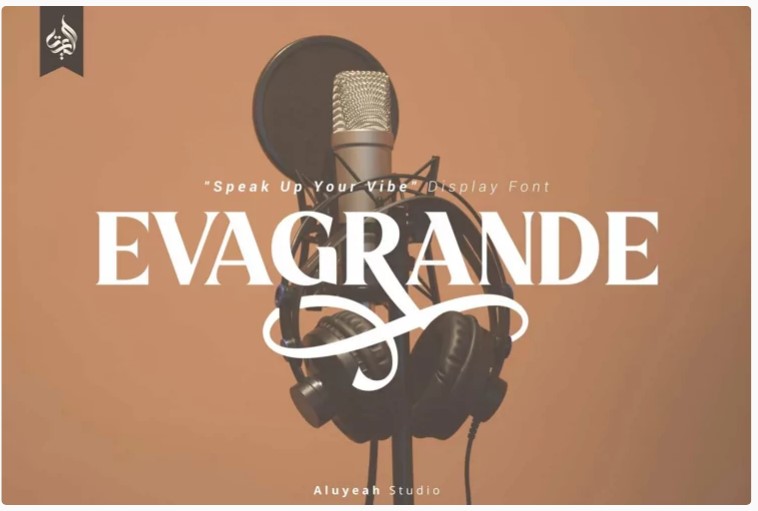
Fontbundles Evagrande Font
[Fontbundles] Evagrande Font
Evagrande, шрифт "Speak Up Your Vibe" с 150+ потрясающими альтернативами.
Очень подходит для журнала, заголовка, веб-сайта, рекламы, упаковки продукта и всех видов дизайнерских проектов, которые у вас есть.